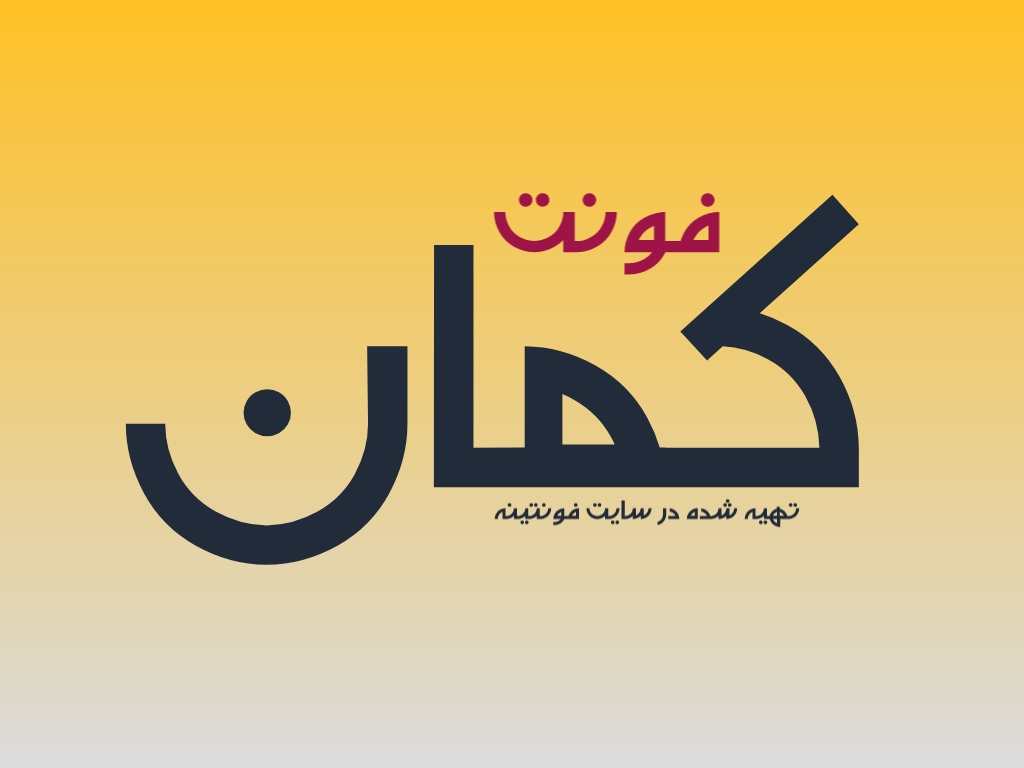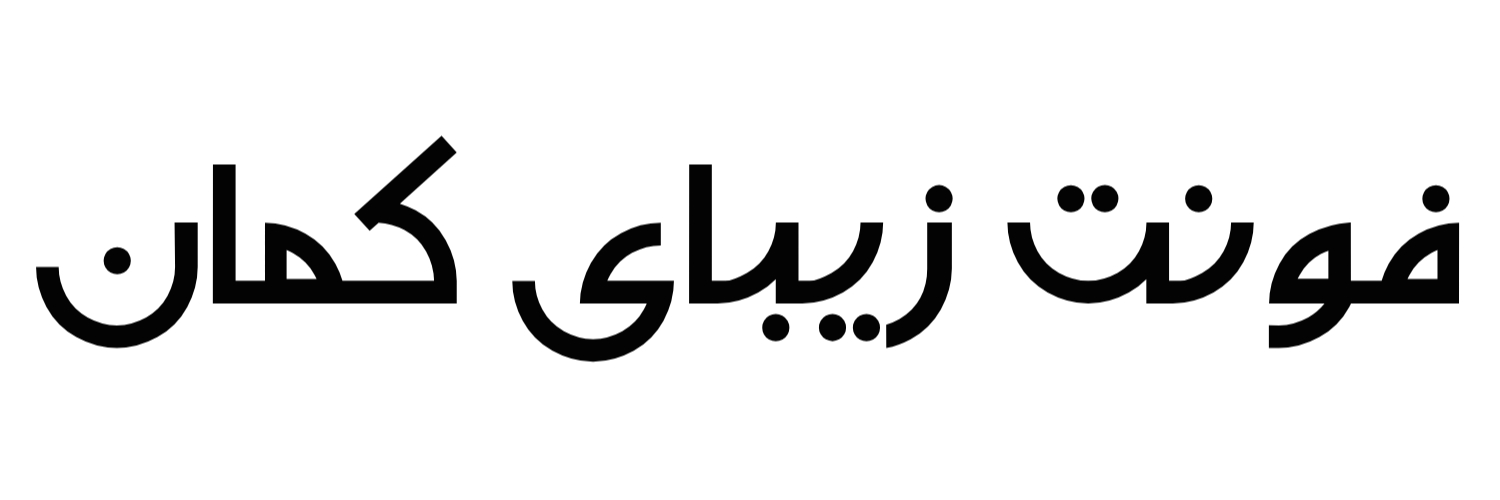
دانلود فونت کمان
دانلود فونت کمان در خدمت شما بزرگورارن هستیم با ارائه فونت زیبا و فارسی کمان این فونت برای طراحی های لوگو و بنر و…. مورد استفاده قرار میگیرد.
ویژگی های فونت :
• مدرن و کاربردی
• زیبا و خاص
• مناسب طراحی لوگو و بنر
تصاویری زیبا از طراحی های خاص با فونت کمان که برای نمایش و نمونه پیش فرضی از نمایش این فونت کاربردی طراحی شده است
فونت زیبای کمان